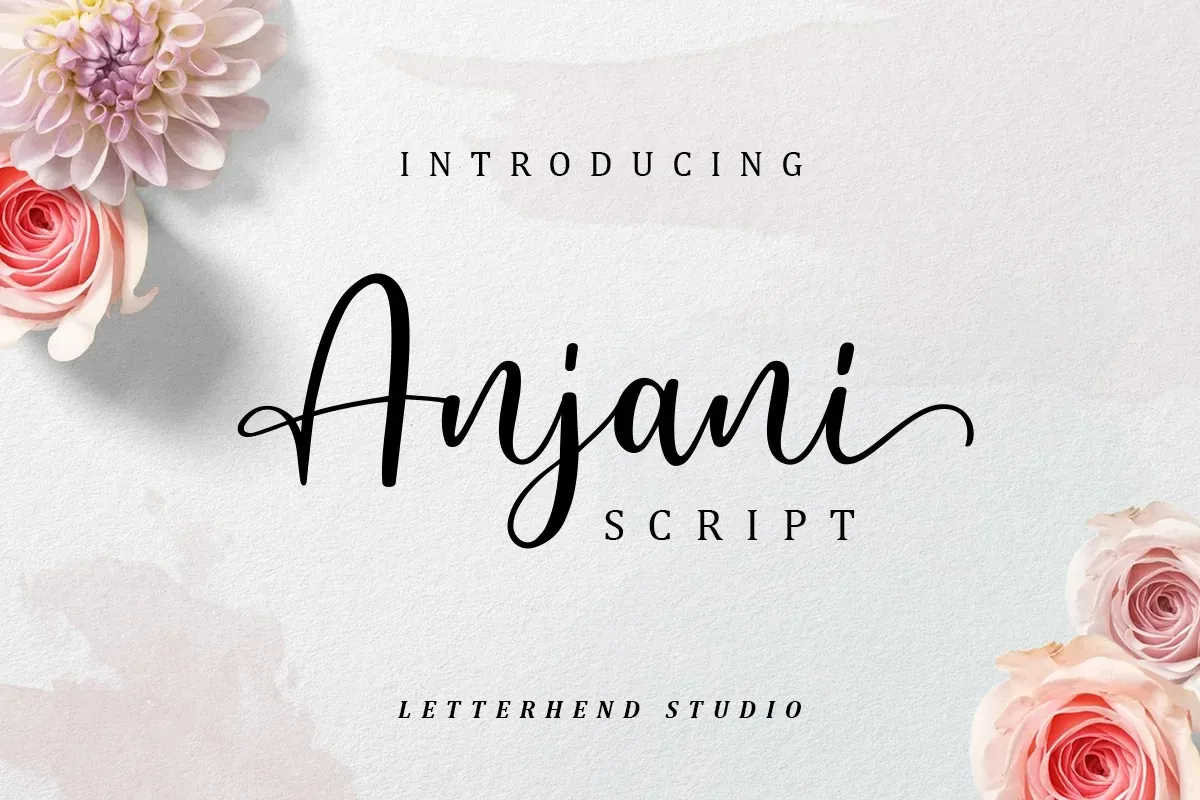
Anjani Font – Fonte Grátis
Anjani Font
Anjani Font é uma elegante tipografia à mão que abraça a essência romântica do handwritten. Criada pelo Studio Letterhend, esta script amigável se adapta perfeitamente para várias necessidades gráficas, desde headlines e logotipos até embalagens de produtos, convites e campanhas publicitárias. Com uma escrita natural e suave, este tipo de letra é versátil o suficiente para atender a vários formatos linguísticos, além de oferecer alternativas estilizadas, ligaturas e suporte a caracteres especiais e numerais. O fato de ser PUA (Unicode) encoded torna-a ainda mais acessível, permitindo que designers brasileiros enriqueçam suas criações com um toque de sofisticação única.